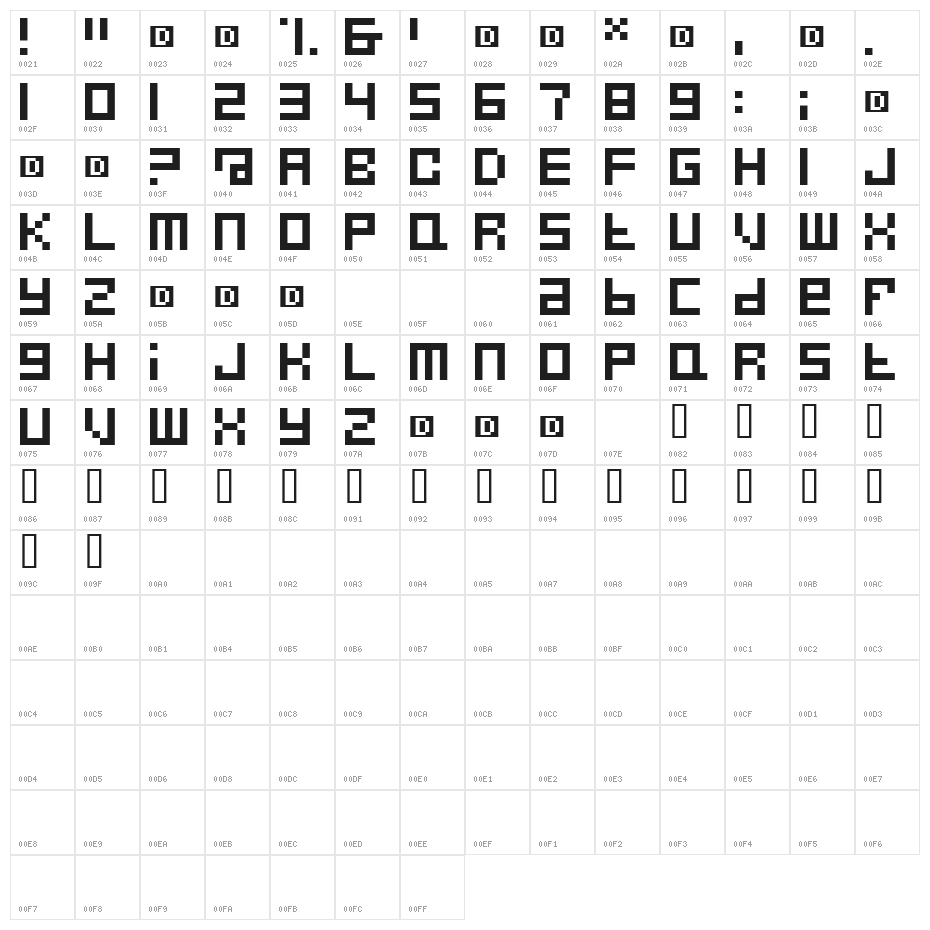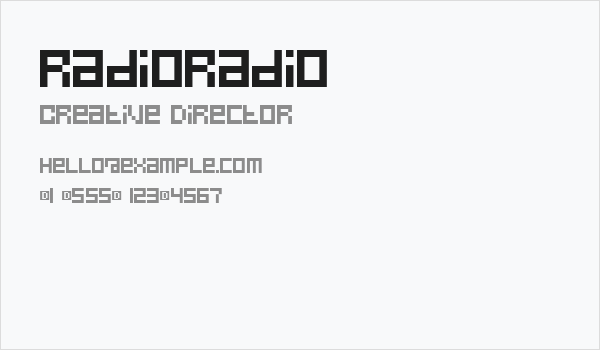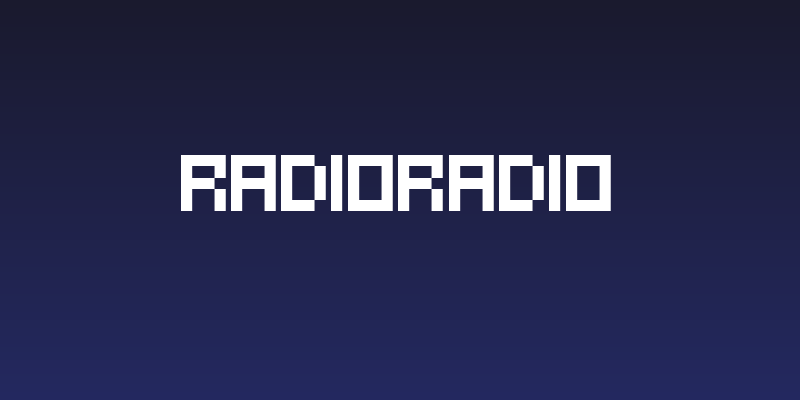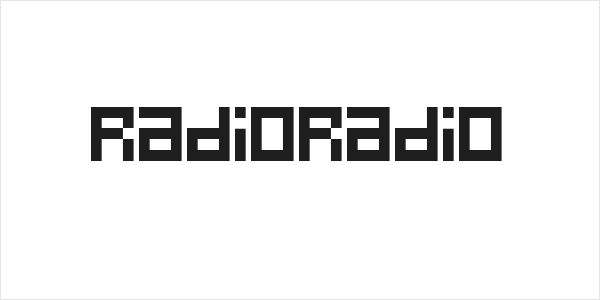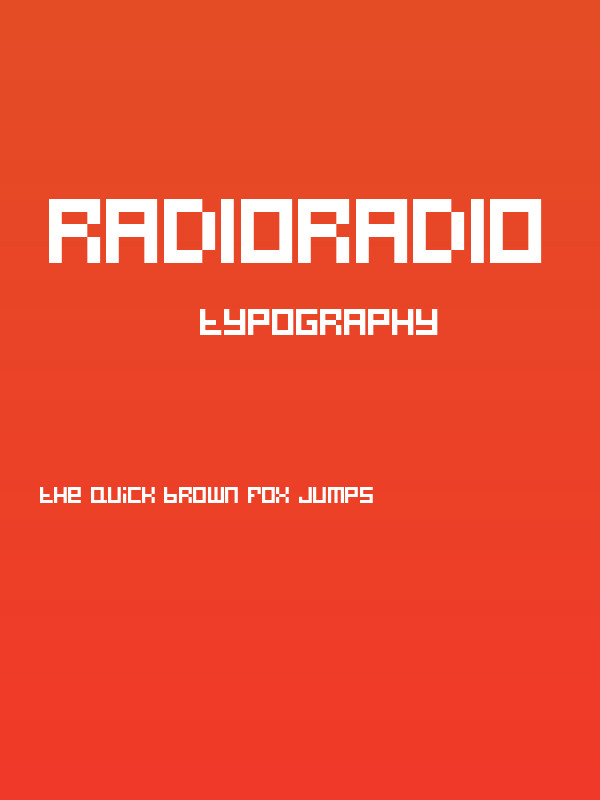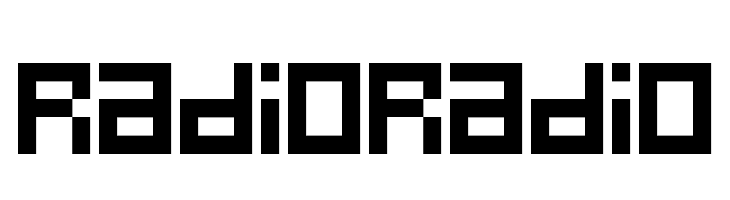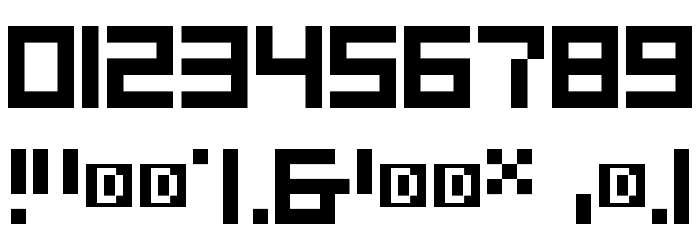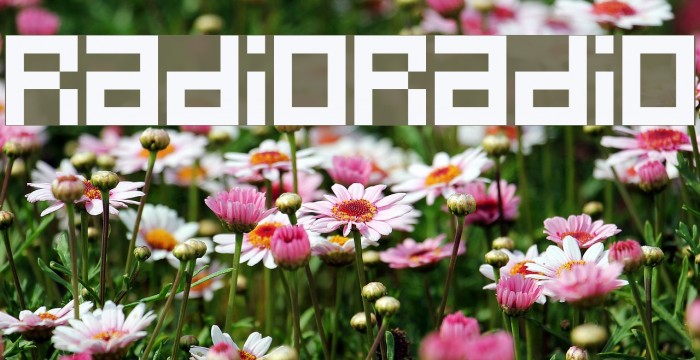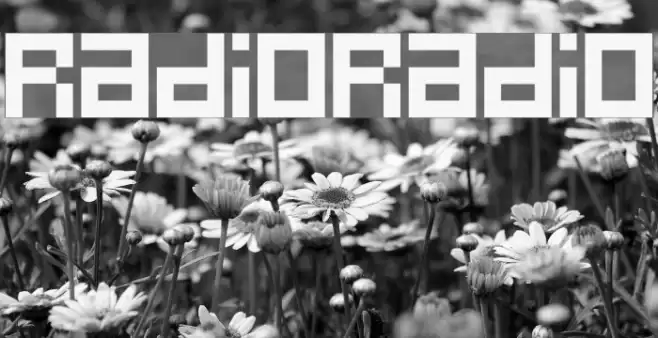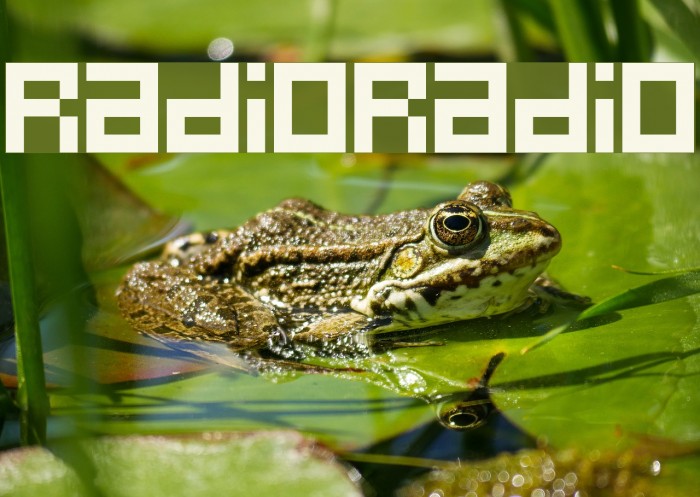
RadioRadio Font
✎ Pixel
| Kategorien | Pixel |
| Anwendungsfall | Headlines, Logos, Digital Displays |
| Vorgeschlagene Projekte | Ideal for digital displays, tech-themed designs, retro gaming graphics, and modern posters. |